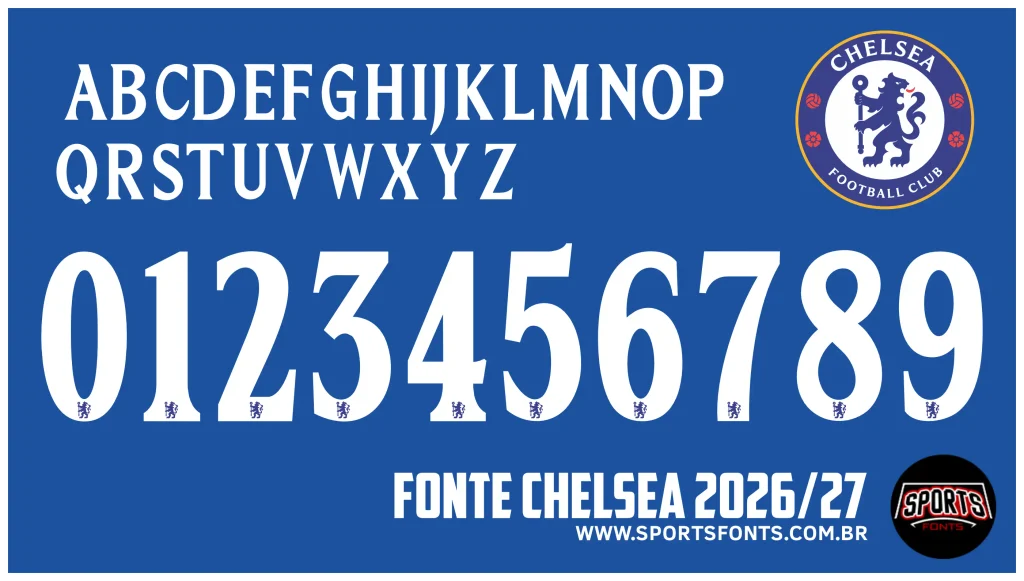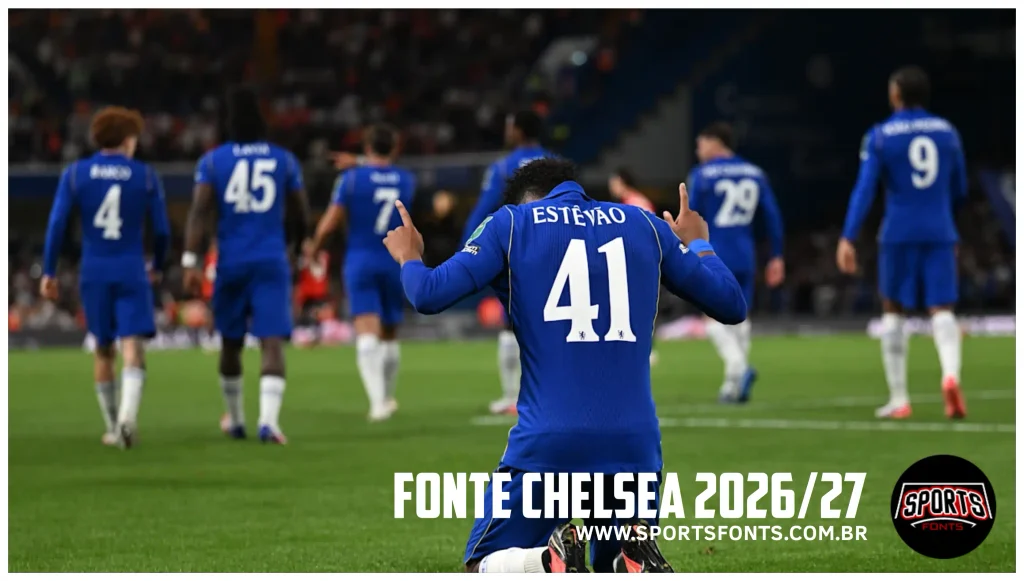
A temporada 2026/27 do Chelsea chegou com uma tipografia nova e bem elegante. A Nike e o clube apostaram em uma fonte serifada com detalhes flareados, que combina perfeitamente com o conceito “Can’t Tame Us” e a valorização do leão rampante.
Nós do Sports Fonts vetorizamos a fonte completa usada nas camisas do Chelsea nesta temporada. O pacote inclui o alfabeto completo (A-Z), números de 0 a 9 com o leãozinho na base de cada número, e suporte a acentos para nomes internacionais.
- Letras maiúsculas
- Números com o leão do Chelsea embutido
- Acentos (Ê, Á, Ó, etc.)